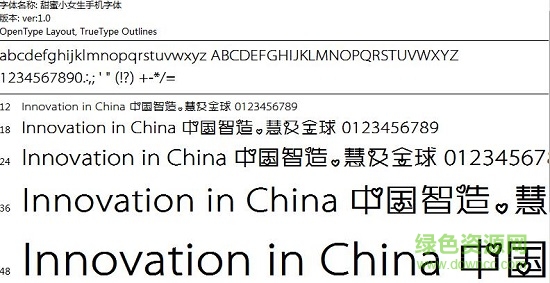
甜蜜小女生字體是一款非常有意思的藝術(shù)字體,這款字體為小女生們精心的準(zhǔn)備的超多甜蜜的小愛(ài)心,讓你的字看上去非常的卡哇伊,喜歡的朋友歡迎下載!
甜蜜小女生字體是一款非??蓯?ài),非常女性化的中文卡通字體,這款字體中的有些筆畫(huà)會(huì)加上愛(ài)心,使得整體看上去會(huì)顯得非常的甜蜜!